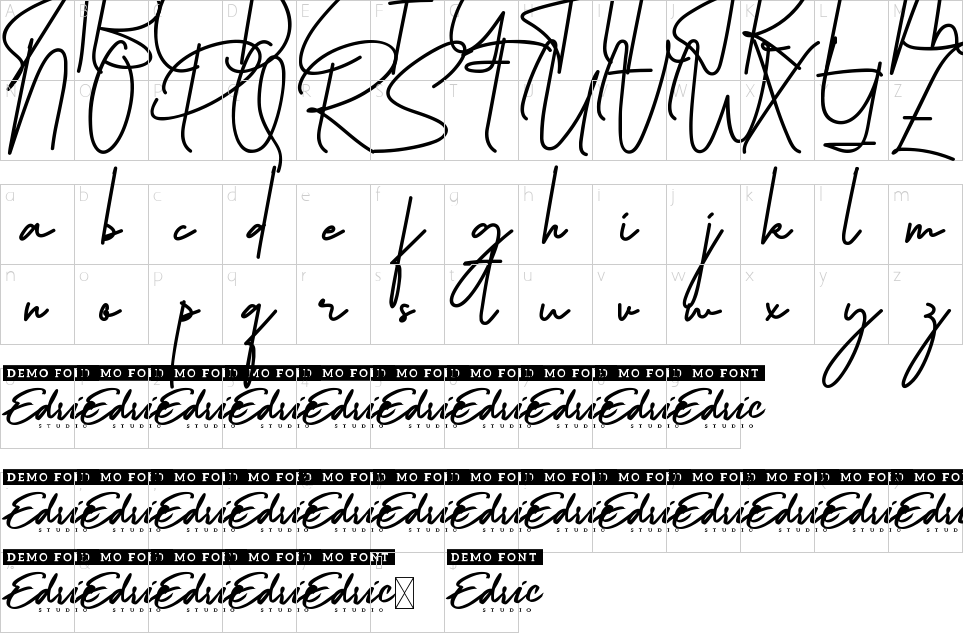
Descubra a beleza única e elegante da Philosophe Signature Font, perfeita para adicionar um toque diferenciado a seus projetos gráficos. Esta elegante fonte foi criada pelo Designer não informado e já foi baixada 5.971 vezes. Com sua tipografia refinada, a Philosophe Signature é uma ótima escolha para personalizar materiais de negócios, como relatórios e apresentações, ou para decorar anúncios e sites. Seja você um designer, um profissional de marketing ou até mesmo um designer de aplicativos móveis, a Philosophe Signature é uma opção de fonte ideal. Instale-a no seu computador hoje e transforme o visual de seus projetos com a elegância e simetria desta fonte.